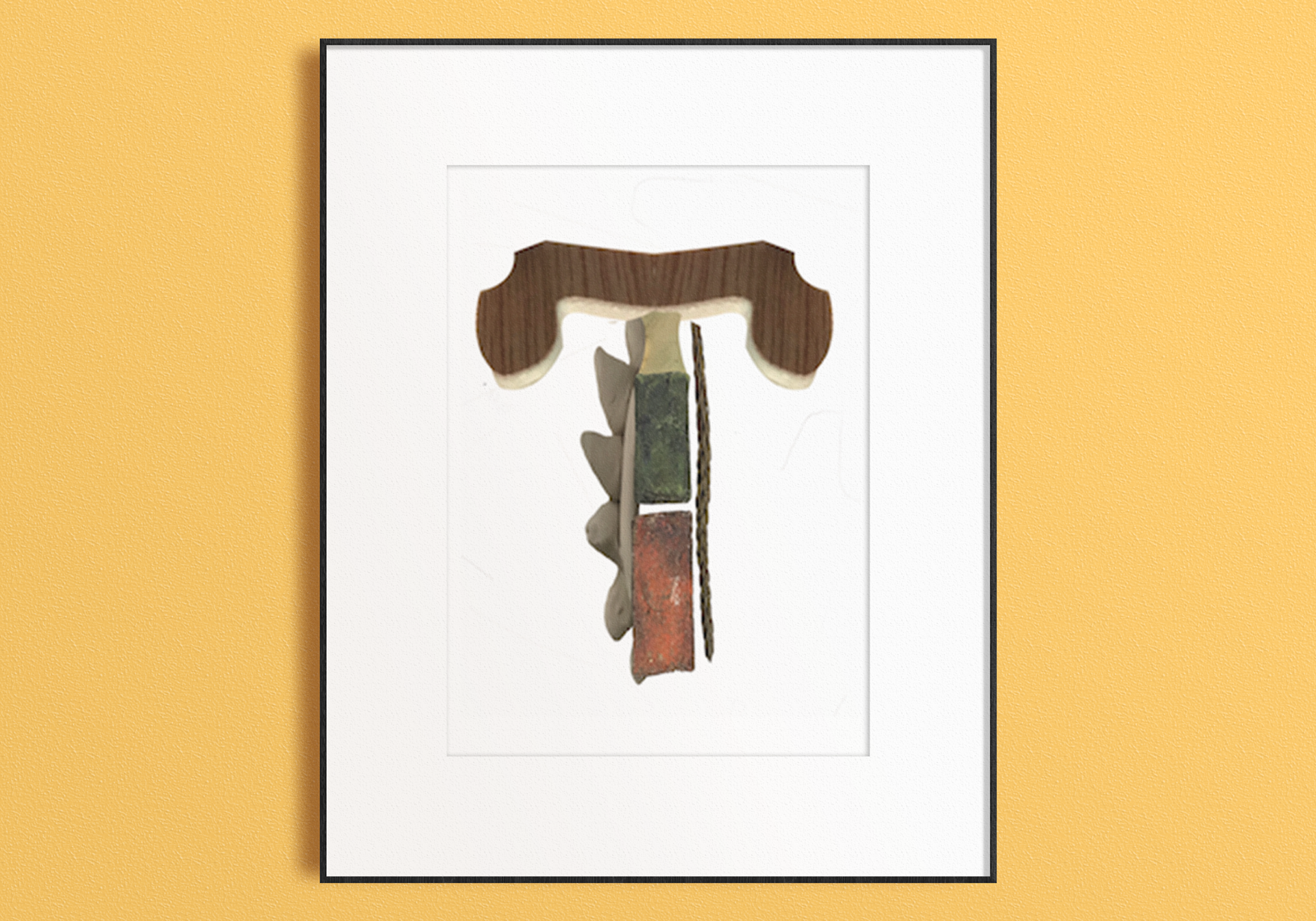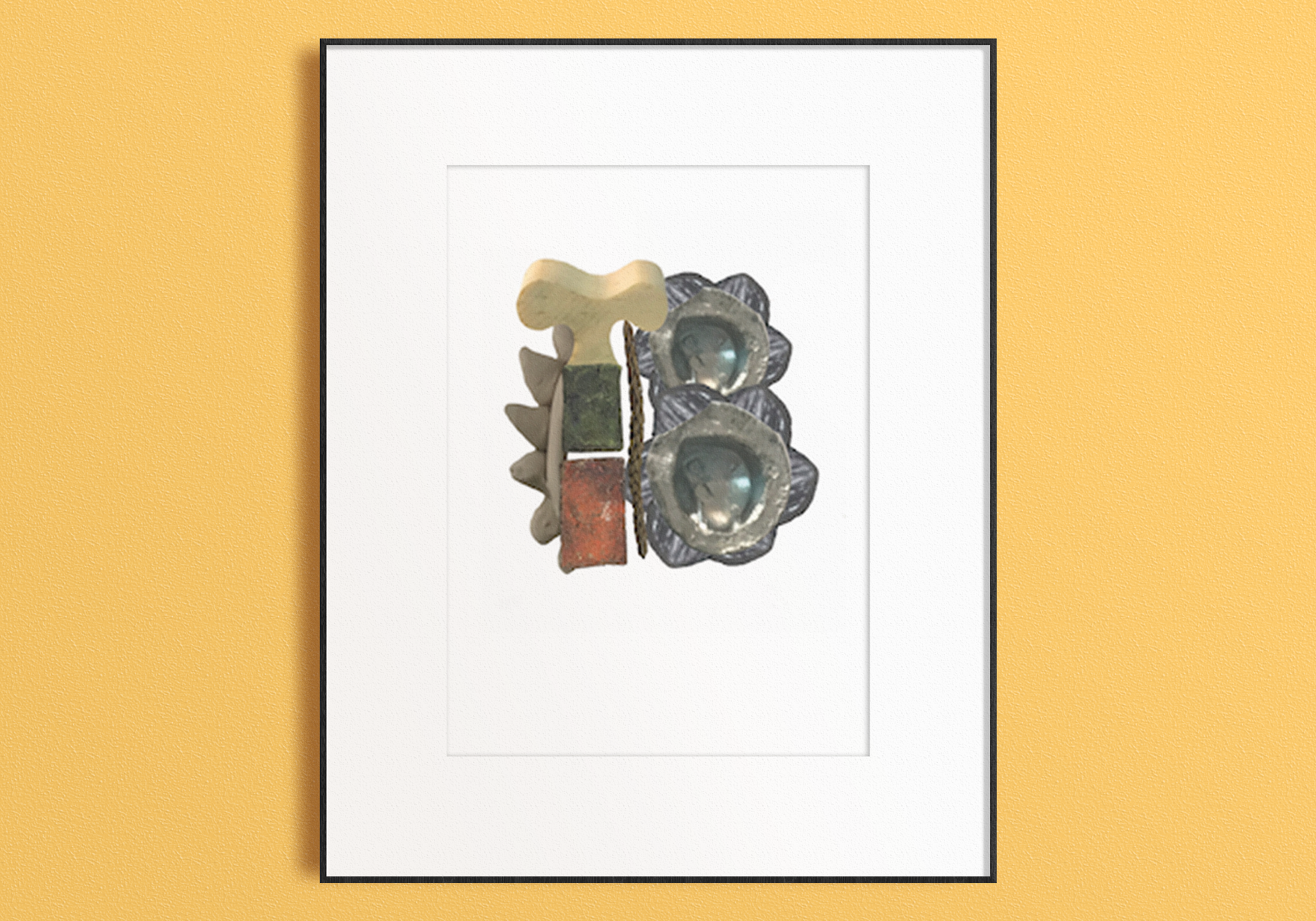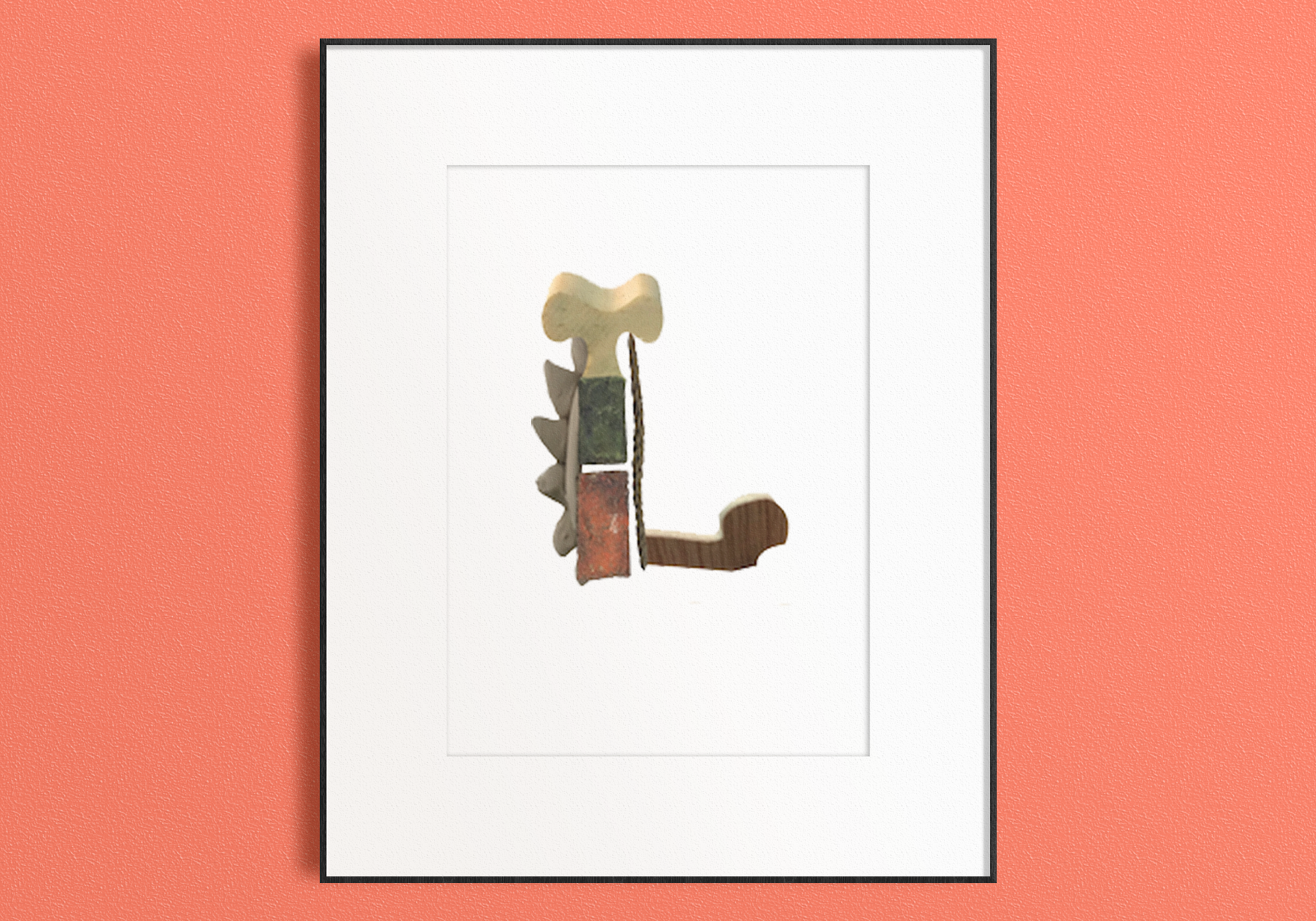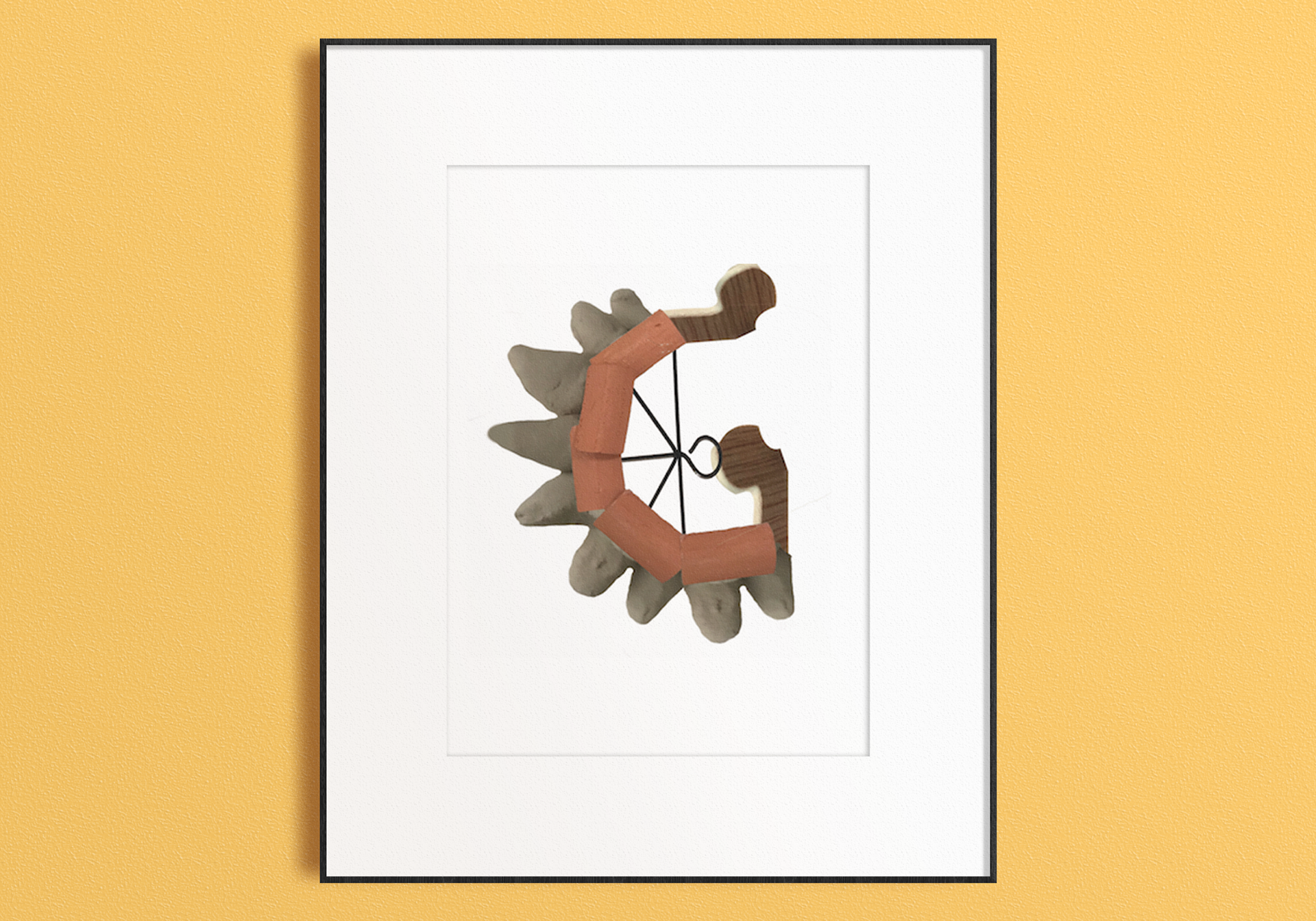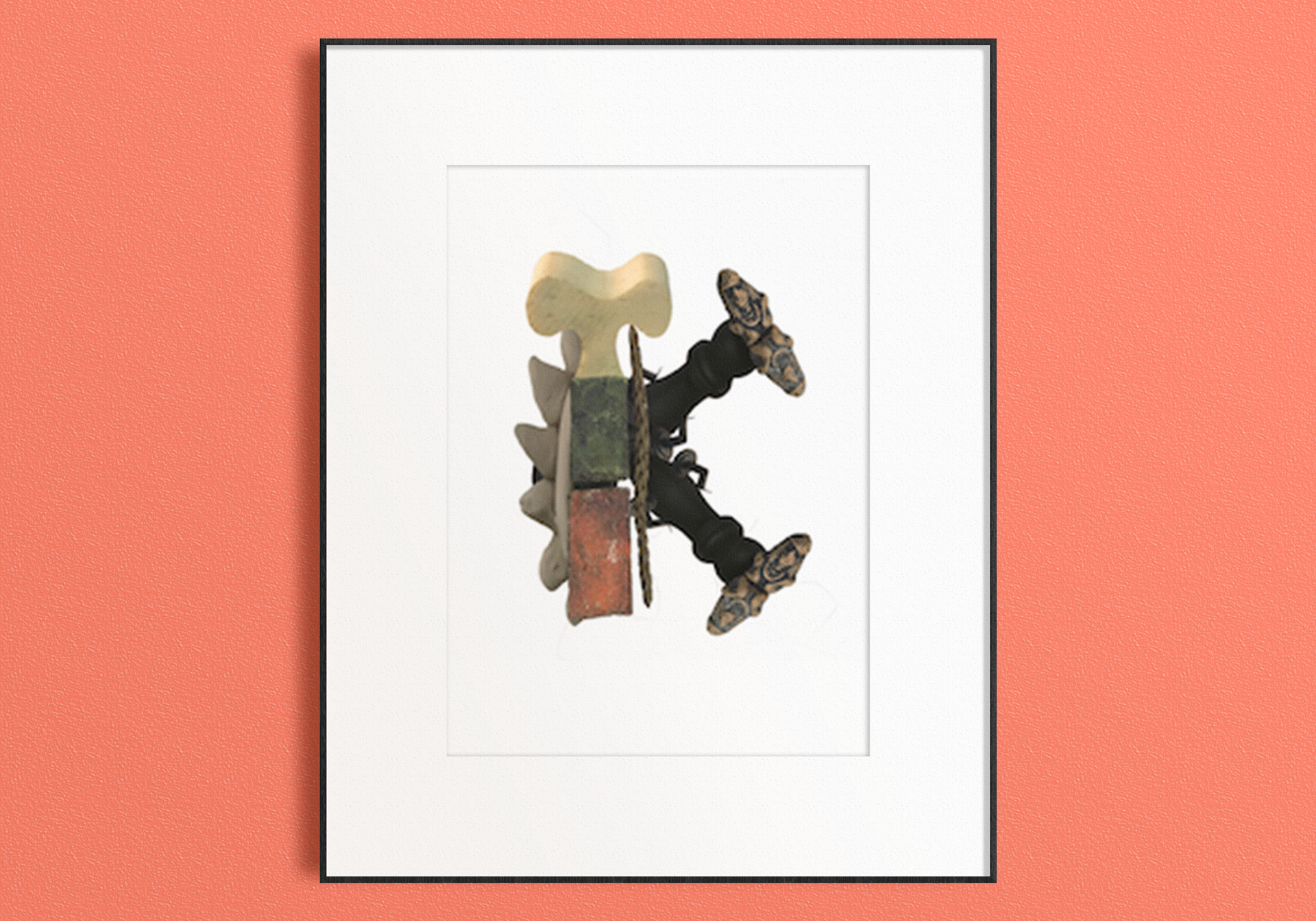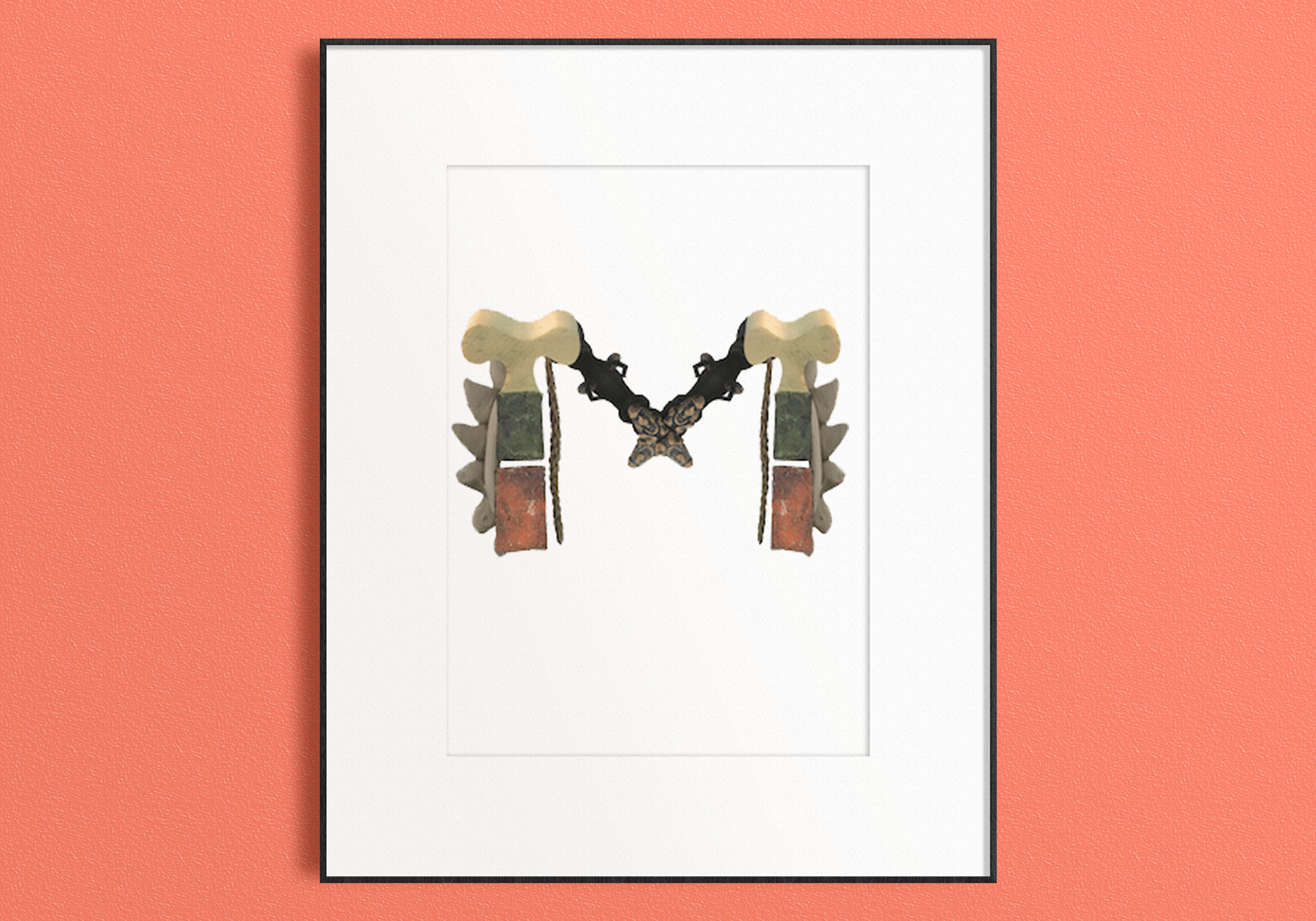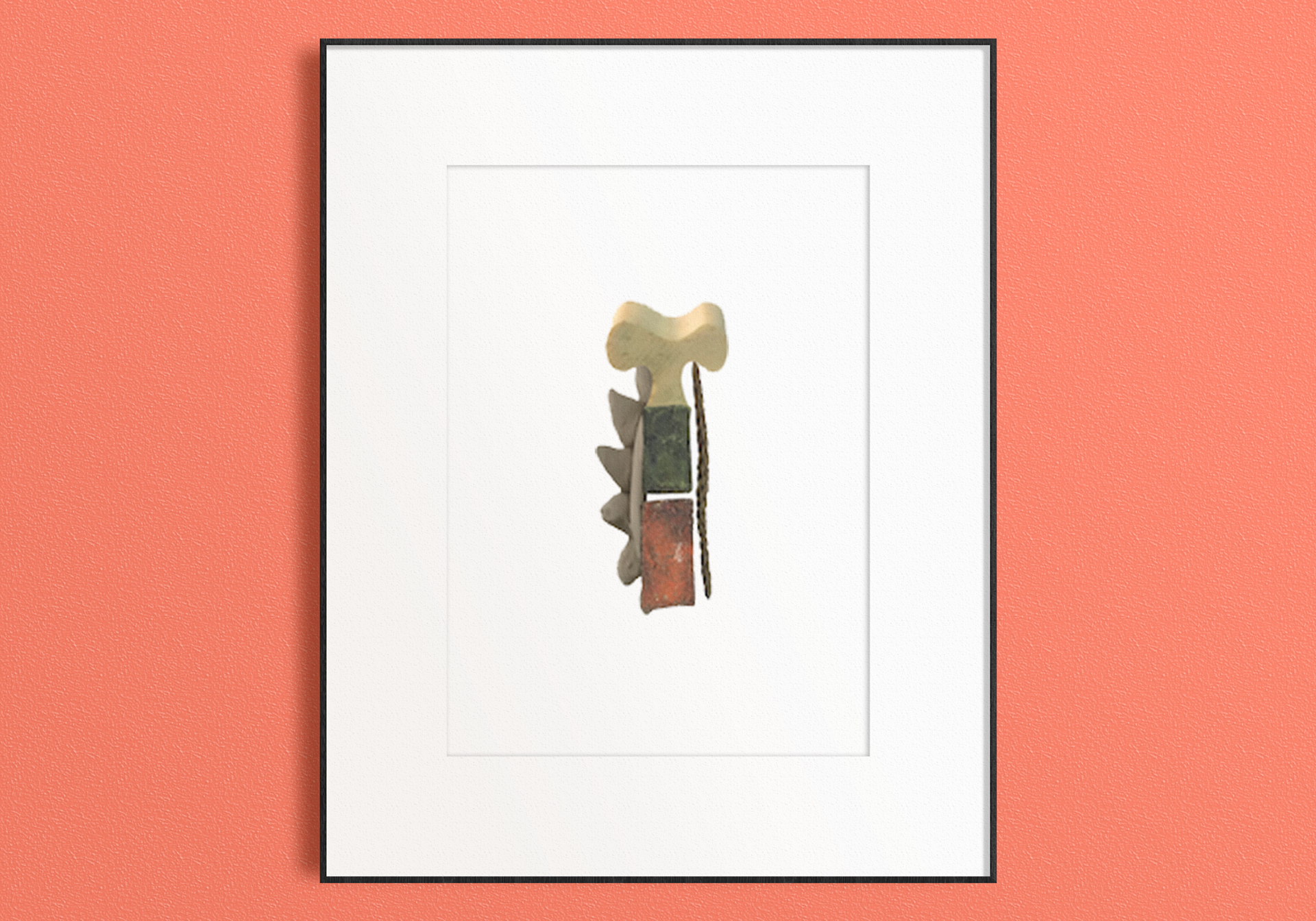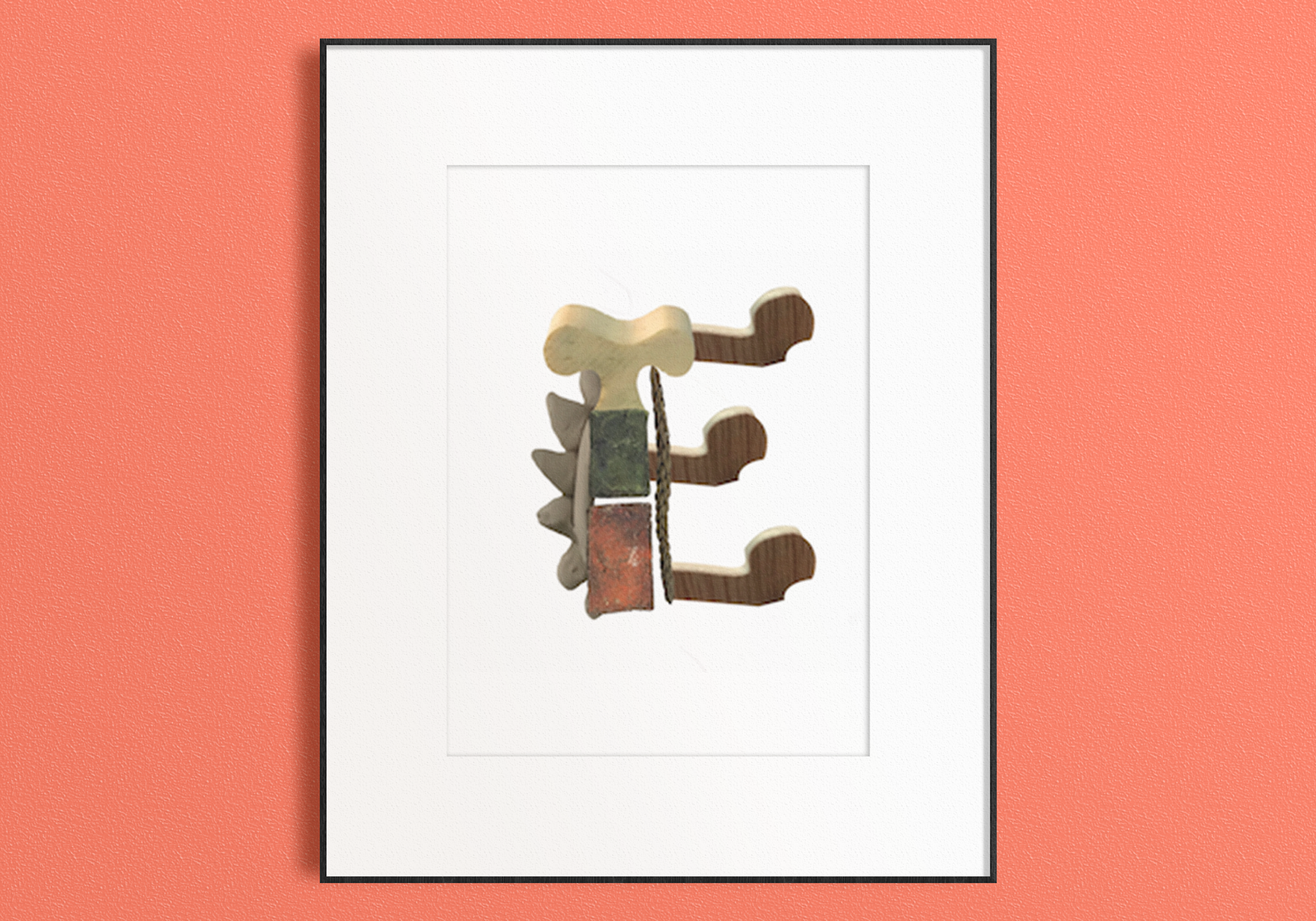
Tipografía Experimental
Basada en la ciudad de villa de leyva conocida por resalta su historia con cronosaurios y fósiles y su bella arquitectura colonial
Tipografía Experimental.